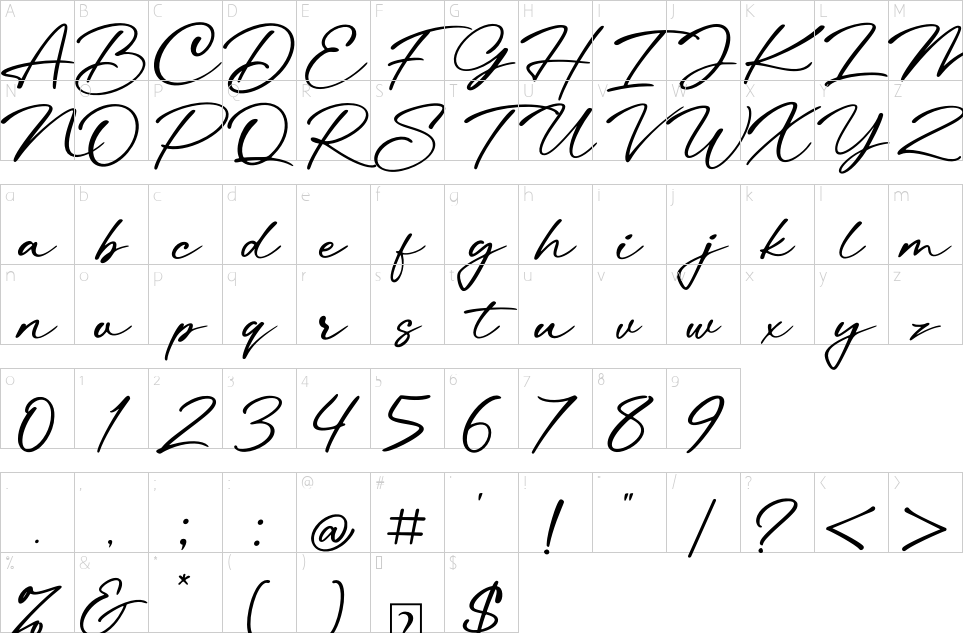
A Sailor Religne é uma fonte moderna e elegante, ideal para designers que buscam uma solução de texto sofisticada para seus projetos. Desenhada por Basnistudio, esta fonte se destaca por sua elegância e facilidade de uso. Com seus traços fluidos e linhas finas, a Sailor Religne é perfeita para criar textos atraentes e impecavelmente legíveis, seja para gráficos digitais, impressões ou designs em linha. Essa fonte foi descarregada 253 vezes e ainda continua agradando os designers que a encontram no catálogo de fontes gratuitas da 1001 Free Fonts. Experimente Sailor Religne e descubra por que muitos utilizam ela para dar vida aos seus trabalhos de design.